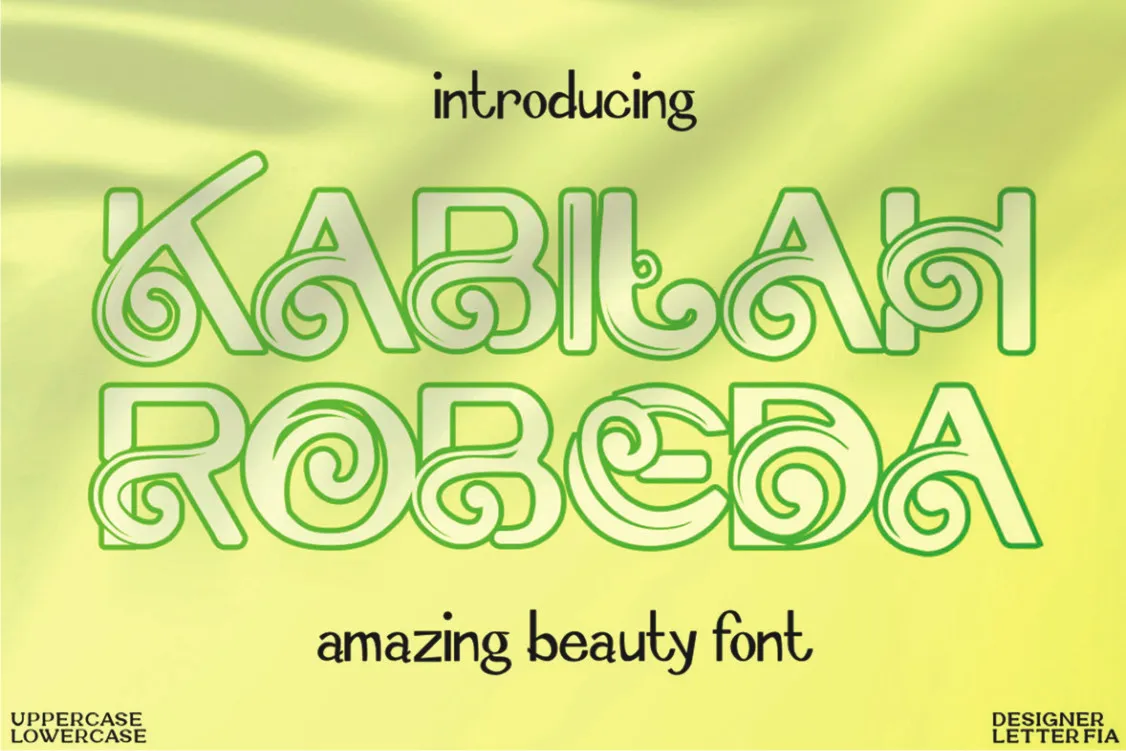
Kabilah Robeda Font – Download Grátis
Esta é uma fonte de exibição cool, trendy e whimsical. Independente do tópico, esta font será um imenso acréscimo à sua biblioteca de fones. Ela tem a capacidade de elevar qualquer criação. Seja ela um site elegante ou um design gráfico audacioso, o Kabilah Robeda Font certamente trará uma identidade visual única e diferenciada. Com seu estilo deslizante e sua personalidade inusitada, esta font é perfeita para aqueles que buscam algo mais do que a estética tradicional. Seja em um design gráfico de alto nível ou em um site pessoal, essa font trará aos seus projetos um toque único e distintivo. Kabilah Robeda Font não apenas reforça o valor intrínseco das suas ideias, mas também lhe dá a liberdade de expressar seu estilo com criatividade. Com uma tipografia que surpreende, ela é perfeita para qualquer projeto que deseja destacar e diferenciar-se da multidão.